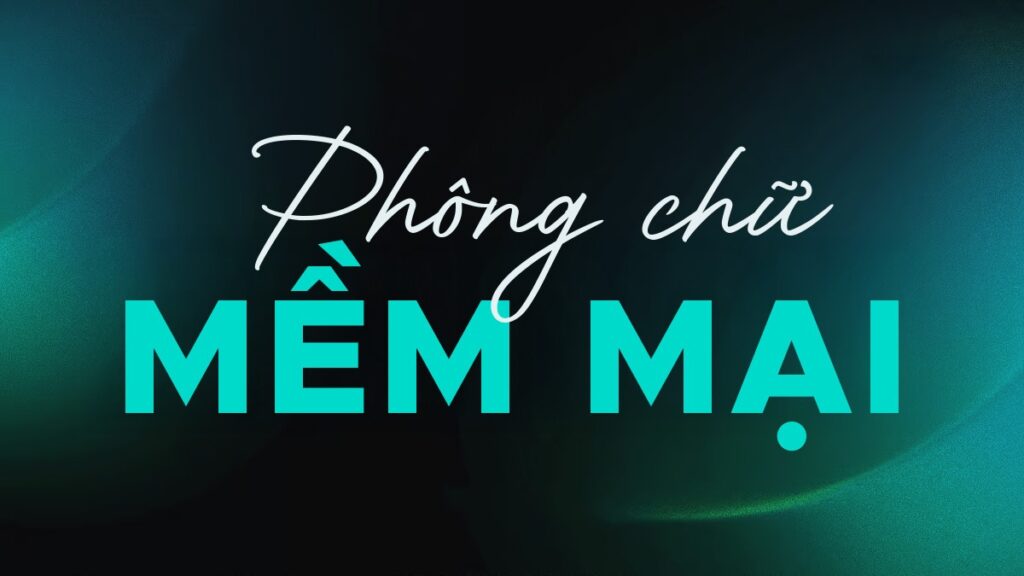
Trong các bản thiết kế kiến trúc và bộ nhận diện thương hiệu, các bộ font chữ mềm mại đóng vai trò quan trọng trong việc cân bằng thị giác, giúp làm dịu đi sự thô cứng của các khối hình học. Với những đường nét uốn lượn tự nhiên và thanh thoát, dòng phông này thường được ưu tiên cho các dự án homestay, quán cafe hoặc trang trí nội thất hiện đại.
Nét đặc trưng thẩm mỹ của dòng font chữ mềm mại trong thiết kế
Điểm lôi cuốn đặc trưng của phông chữ mềm mại nằm ở sự biến thiên linh hoạt của các nét thanh và nét đậm, mô phỏng nhịp điệu của nét bút thủ công. Khác với kiểu chữ hệ thống cứng nhắc, dòng font này mang lại cảm giác thư thái, lãng mạn và đầy tính nhân bản cho văn bản. Việc sử dụng phiên bản font chữ mềm mại Việt hóa giúp người dùng giải quyết triệt để tình trạng lỗi dấu thanh, đảm bảo các ký tự đặc biệt như “đ, ă, ơ” phối hợp hài hòa với khung chữ chính, duy trì nhịp điệu thẩm mỹ ổn định.
Sự ổn định về mặt thị giác của font mềm mại còn giúp thương hiệu xây dựng lòng tin thông qua vẻ ngoài chỉn chu. Trong kiến trúc, những đường cong tinh tế của phông chữ thường được dùng để đối trọng với sự góc cạnh của các khối nhà lắp ghép hay văn phòng container, tạo nên một tổng thể hài hòa và giàu cảm xúc. Đây là lựa chọn phù hợp để định hình phong cách cho các dự án nghỉ dưỡng xanh hoặc những không gian sống đề cao gu thẩm mỹ cá nhân và sự tinh tế.
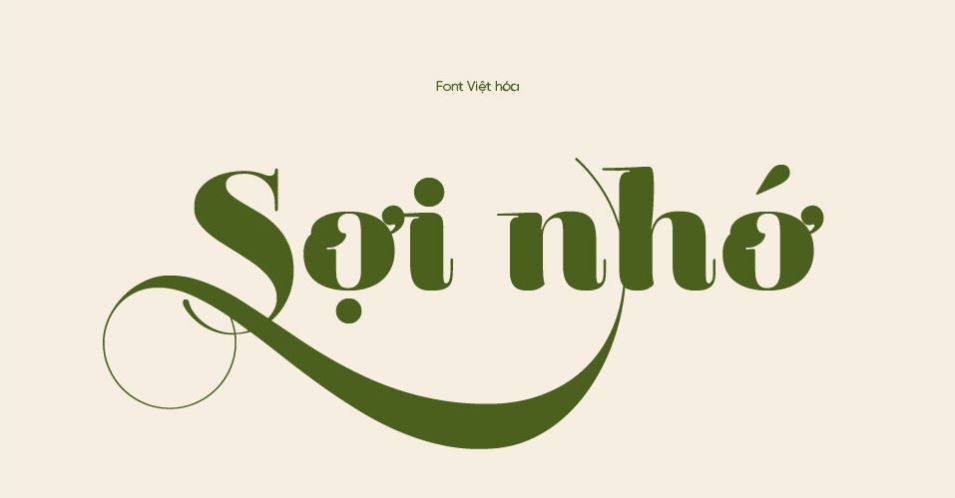
| Phân loại phong cách | Script / Calligraphy / Handwritten |
| Nhóm phông tiêu biểu | Darleston, Great Vibes, Dancing Script, SVN-Bali |
| Mục đích phù hợp | Logo homestay, thiệp mời, decor nội thất |
Tư vấn lựa chọn: Để bản thiết kế đạt được hiệu quả thị giác chuyên nghiệp, bạn nên sử dụng font mềm mại Việt hóa cho các tiêu đề chính hoặc câu slogan. Việc phối hợp cùng một phông chữ không chân (Sans-serif) tối giản cho phần nội dung mô tả chi tiết sẽ giúp tổng thể bố cục trông khoa học và dễ đọc hơn.
03 Ứng dụng phông chữ mềm mại vào thực tế công trình
Nhờ diện mạo giàu tính nghệ thuật và cá tính riêng, bộ phông chữ này mang lại giá trị cao trong khâu trang trí và quảng bá các công trình hiện đại:
- Hệ thống nhận diện cho Homestay & Boutique Hotel: Những nét chữ mềm mại rất ăn ý khi xuất hiện trên biển hiệu gỗ khắc laser hoặc mica gương gương tại các khu nhà lắp ghép nghỉ dưỡng. Font chữ này giúp không gian toát lên vẻ thư thái, thu hút du khách yêu thích phong cách sống xanh.
- Trang trí không gian nội thất nghệ thuật: Bạn có thể dùng font này để làm tranh quotes trang trí hoặc cắt chữ nổi đèn neon tại phòng khách, sảnh chờ văn phòng nhằm tạo điểm nhấn lôi cuốn và khơi gợi cảm hứng cho người sử dụng không gian.
- Thiết kế hồ sơ năng lực dự án: Sử dụng font chữ mềm mại sang trọng cho các lời nhắn gửi hoặc tiêu đề trang bìa giúp thể hiện sự tận tâm và phong cách làm việc chuyên nghiệp của đơn vị kiến tạo đối với đối tác và khách hàng.
03 Lưu ý để bố cục font chữ mềm mại sang trọng và chuyên nghiệp
Để khai thác hiệu quả vẻ đẹp của dòng font đặc thù này mà không làm rối mắt người xem, người thiết kế nên lưu tâm một số kinh nghiệm sau:
- Kiểm soát khoảng cách dòng: Do cấu trúc chữ mềm mại thường có các nét móc vươn rộng, bạn nên nới rộng khoảng cách giữa các dòng để các ký tự không bị chồng lấn, giữ được sự minh bạch cho văn bản khi nhìn từ xa.
- Hạn chế viết hoa toàn bộ ký tự: Đặc trưng của dòng font script là sự liên kết nhịp nhàng giữa các chữ cái viết thường. Việc viết hoa toàn bộ cụm từ sẽ làm mất đi tính nhịp điệu tự nhiên và khiến tiêu đề trở nên thô cứng, thiếu thẩm mỹ.
- Kiểm tra hiển thị ở kích thước nhỏ: Các phông chữ có đường nét quá mảnh và uốn lượn có thể bị nhòa mờ khi in ấn ở kích thước nhỏ. Bạn nên kiểm tra độ sắc nét của bản in thử để điều chỉnh độ dày nét phù hợp.